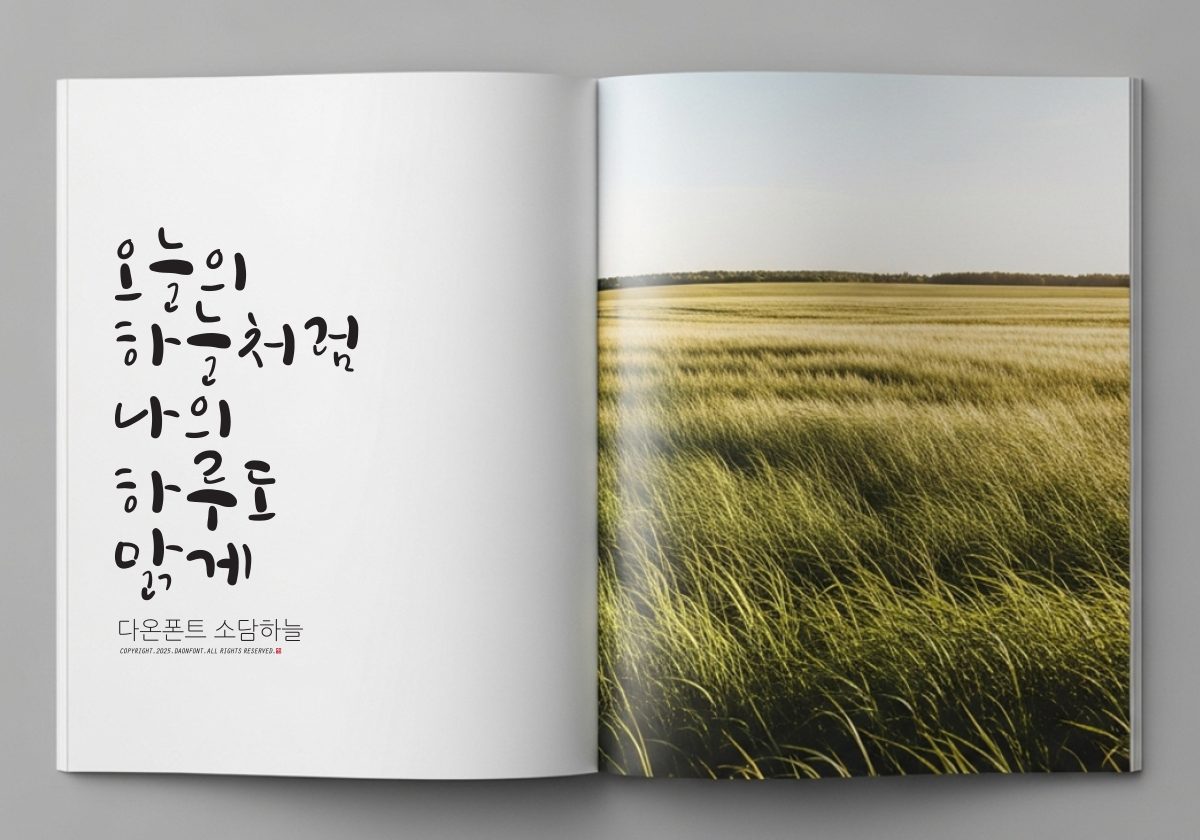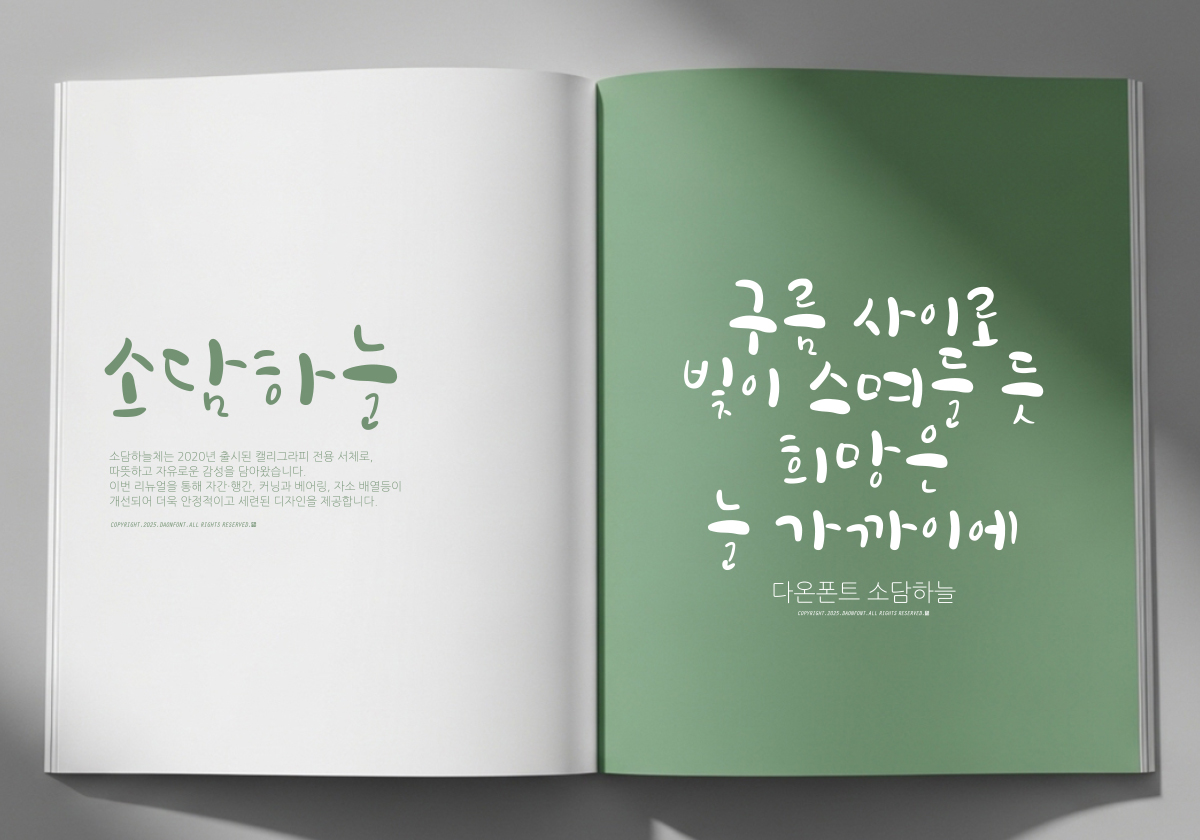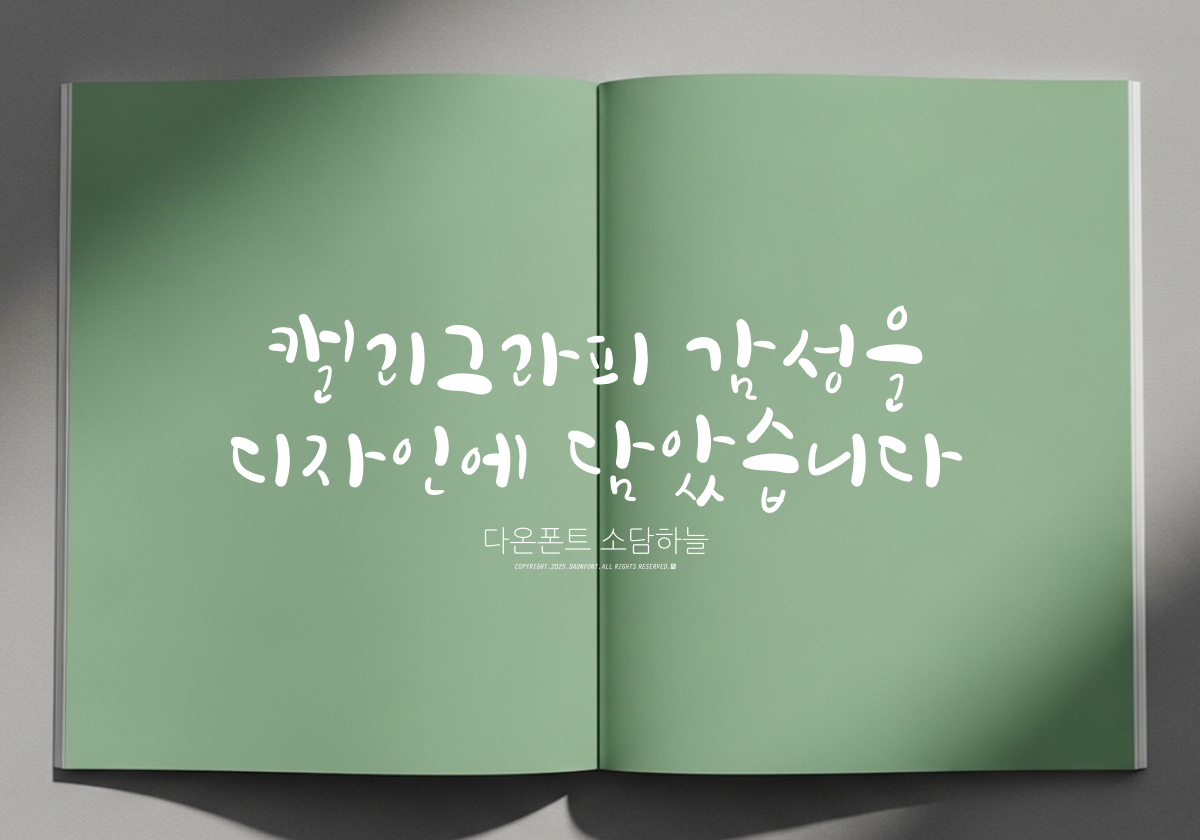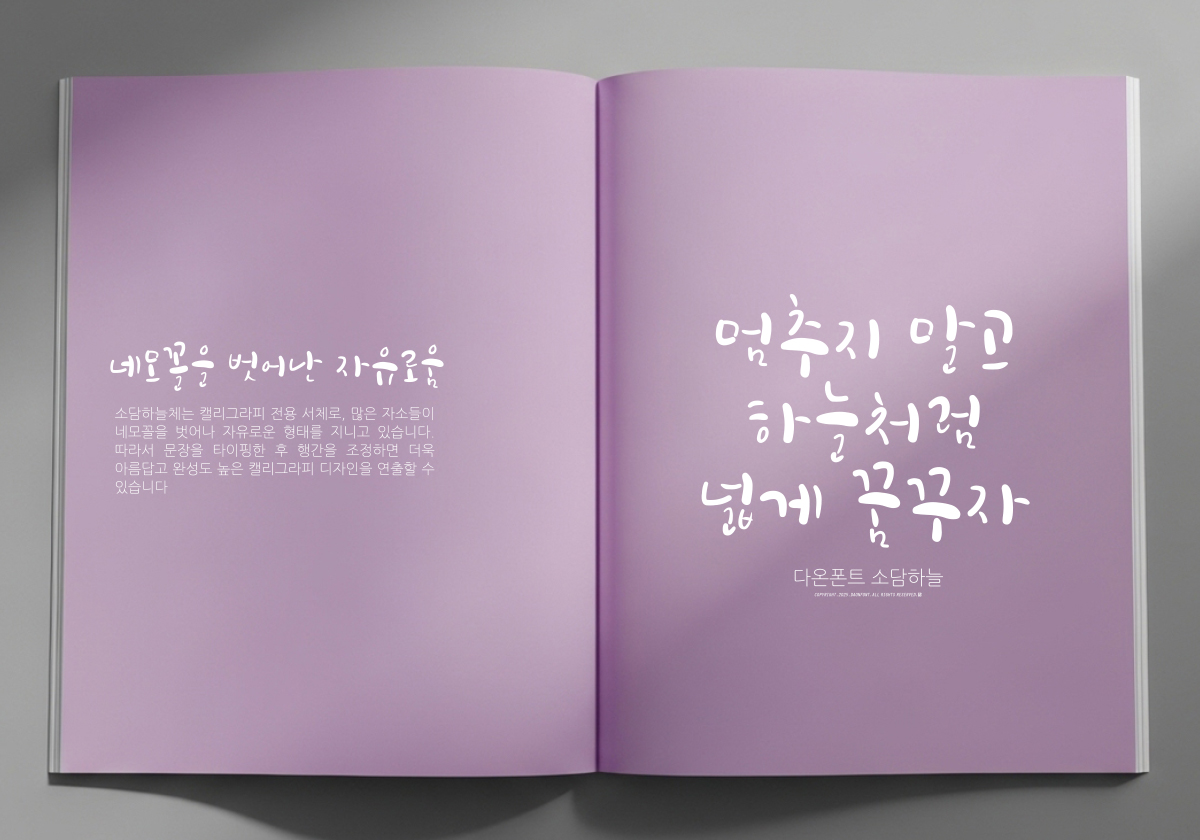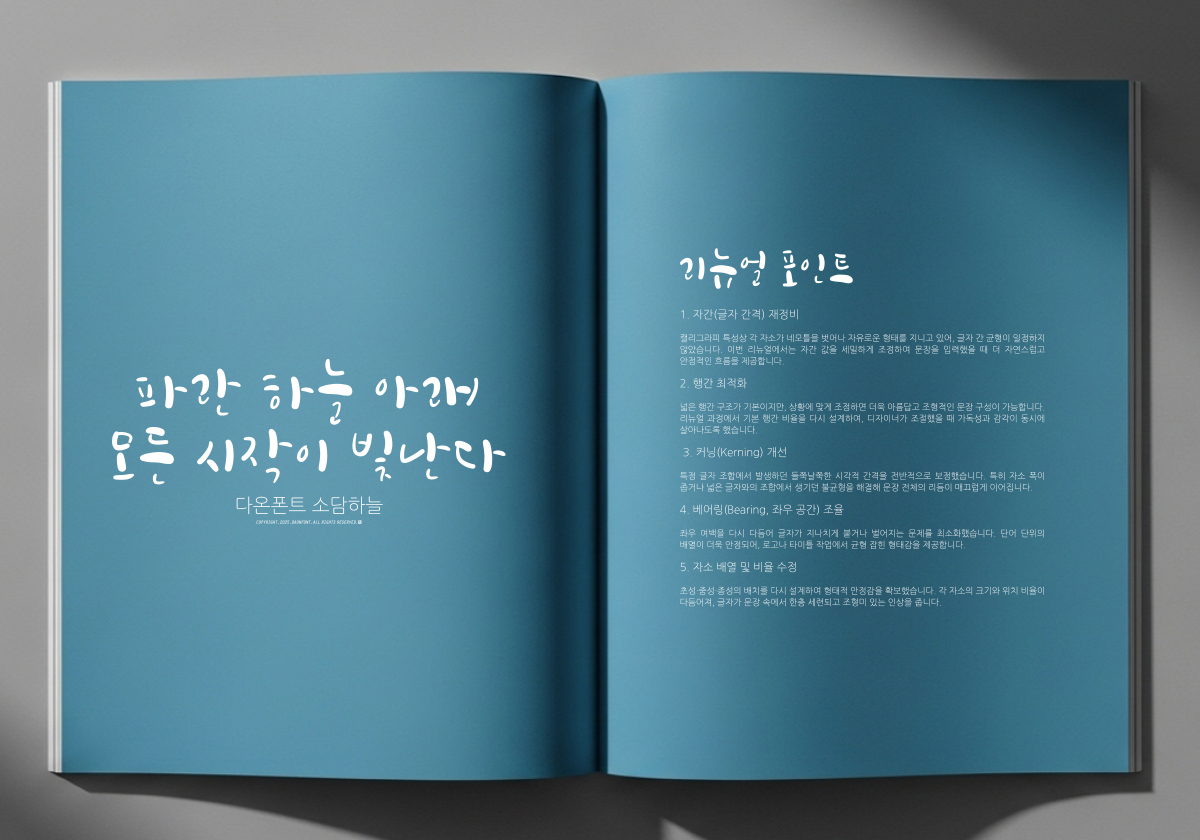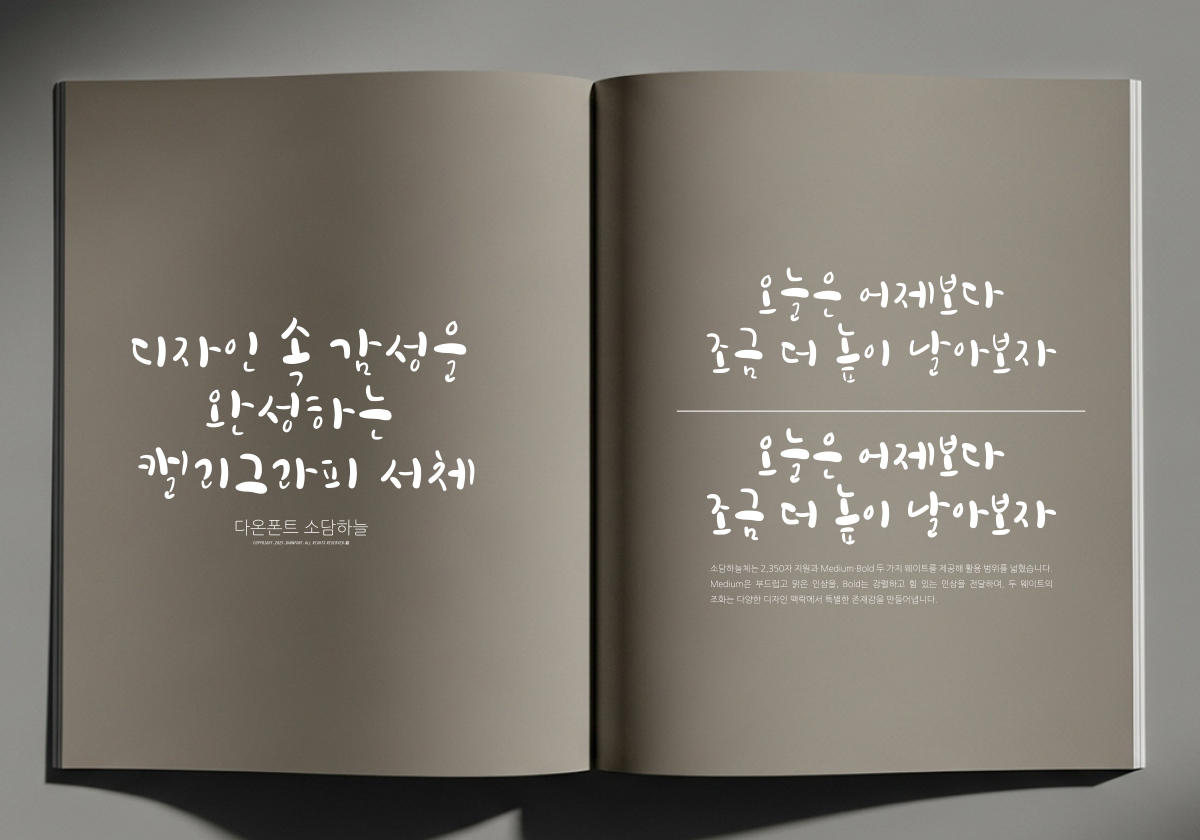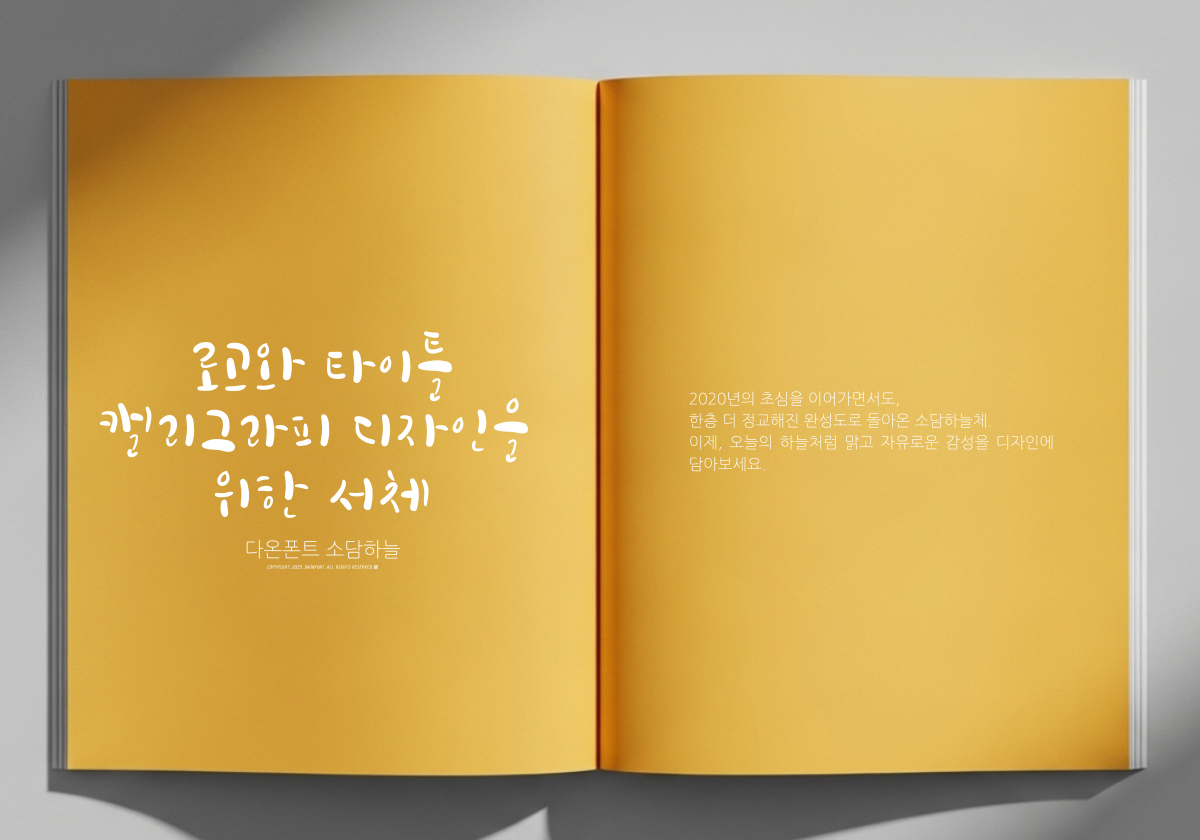
다온폰트 '소담하늘' 리뉴얼 안내
2020년에 출시된 캘리그라피 전용 서체 ‘소담하늘체’가
한층 정교하게 다듬어진 리뉴얼 에디션으로 돌아왔습니다.
이번 리뉴얼에서는 넓은 자간과 행간, 그리고 개선된 커닝과 배열을 통해
보다 감각적이고 완성도 높은 캘리그라피 디자인을 구현할 수 있습니다.
맑은 하늘처럼 자유롭고 따뜻한 글자, 소담하늘체.
2020년 첫 출시 이후 새롭게 정제된 리뉴얼 버전을